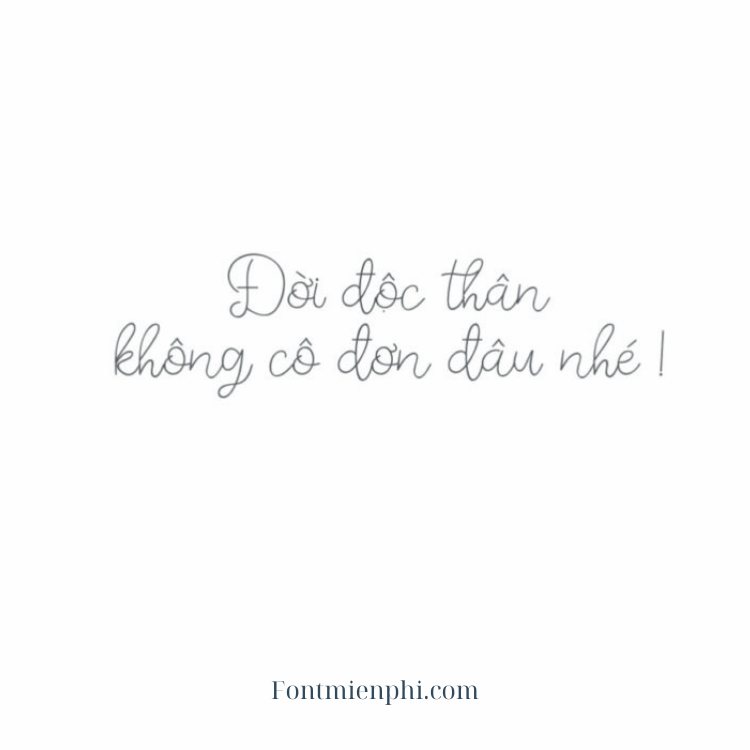
Font Việt hóa VIP Memory of 2018 , Font cho Valentine
• Tác giả:  Khurasan
• Việt hóa:  fonttiengviet.com
Giới thiệu về Font Việt hóa VIP Memory of 2018 , Font cho Valentine
Trong thiết kế đồ họa hiện đại, việc lựa chọn một bộ Font Miễn Phí chất lượng luôn là ưu tiên hàng đầu của các nhà sáng tạo. Đặc biệt, bộ Font Việt hóa VIP Memory of 2018 , Font cho Valentine nổi lên như một lựa chọn hoàn hảo cho những ai đang tìm kiếm sự kết hợp giữa nét hoài cổ và sự lãng mạn tinh tế. Bộ font này được tinh chỉnh kỹ lưỡng với đầy đủ dấu tiếng Việt, giúp bạn dễ dàng ứng dụng vào các dự án thiệp mừng, bìa sách hay các ấn phẩm truyền thông nhân dịp lễ tình nhân.
Đặc điểm nổi bật của Font Việt hóa VIP Memory of 2018
Bộ phông chữ này mang phong cách viết tay mềm mại, tạo cảm giác gần gũi và đầy cảm xúc. Với các đường nét thanh mảnh nhưng chắc chắn, nó giúp truyền tải thông điệp yêu thương một cách trọn vẹn nhất. Đây không chỉ là công cụ thiết kế mà còn là phương tiện để lưu giữ những kỷ niệm đẹp của năm 2018 và lan tỏa hơi ấm trong mùa Valentine ngọt ngào.
Cách ứng dụng Font cho Valentine trong thiết kế học đường
Đối với các bạn học sinh và giáo viên, việc sử dụng Font Việt hóa VIP Memory of 2018 , Font cho Valentine sẽ làm cho các bài thuyết trình hoặc báo tường trở nên sinh động hơn. Bạn có thể dùng font này để thiết kế những tấm thiệp tri ân, trang trí bảng tin lớp học hoặc làm tiêu đề cho các video kỷ niệm của tập thể lớp.
Lưu ý khi sử dụng font chữ thiết kế
Khi sử dụng bộ font này, bạn nên kết hợp với những tông màu nhẹ nhàng như hồng pastel, đỏ rượu hoặc trắng để làm nổi bật chủ đề tình yêu. Sự hài hòa giữa màu sắc và kiểu chữ sẽ tạo nên một tác phẩm nghệ thuật ấn tượng, thu hút người xem ngay từ cái nhìn đầu tiên.
Kết luận về bộ font chữ kỷ niệm